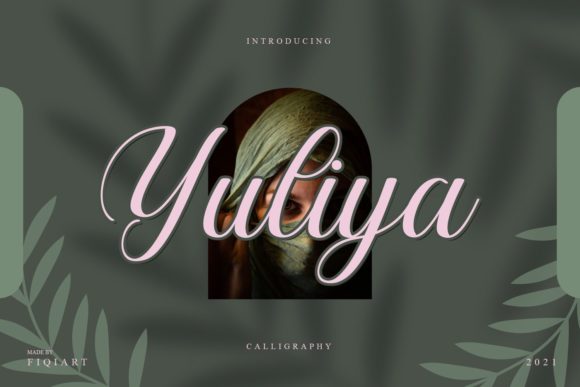
Creativefabrica Yuliya Font 2021
[Creativefabrica] Yuliya Font (2021)
Yuliya - это нежный, элегантный и плавный рукописный шрифт.
Влюбитесь в его восхитительный стиль и используйте его для создания великолепных свадебных приглашений, красивых канцелярских товаров, привлекательных постов в социальных сетях и многого другого!